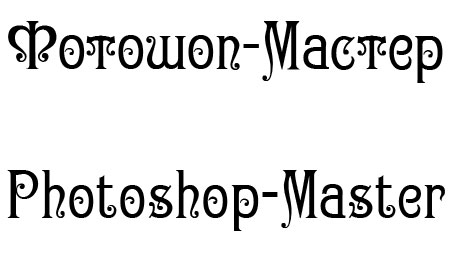
Дополнения Шрифты Татьяна Гапонова 19 марта 2009 Шрифт - Gertruda Victoriana Красивый шрифт с поддержкой русского языка Скачать Шрифт - Gertruda Victoriana
очень интересный